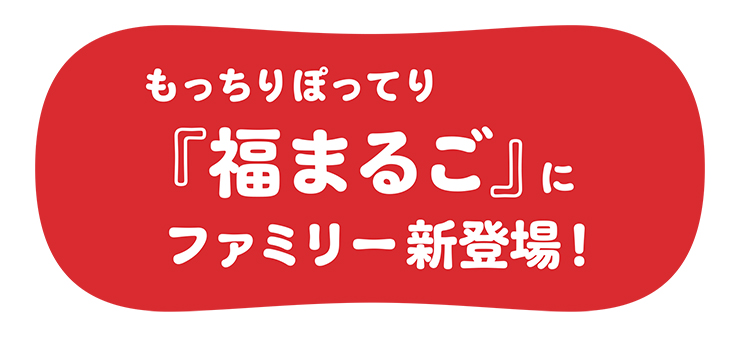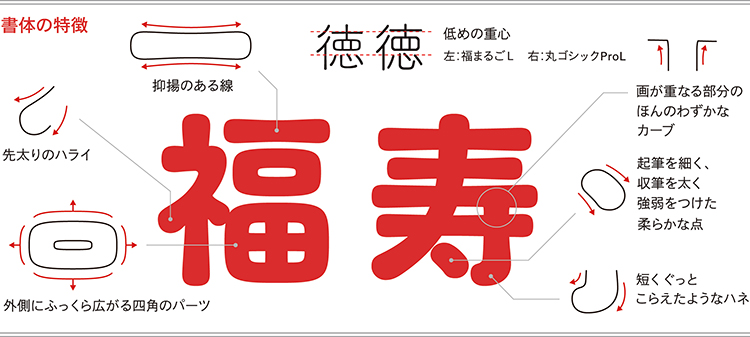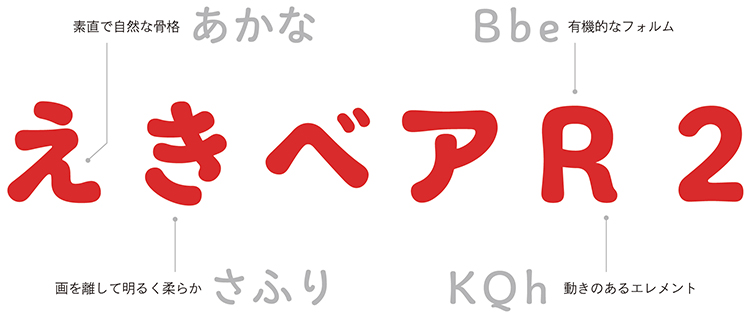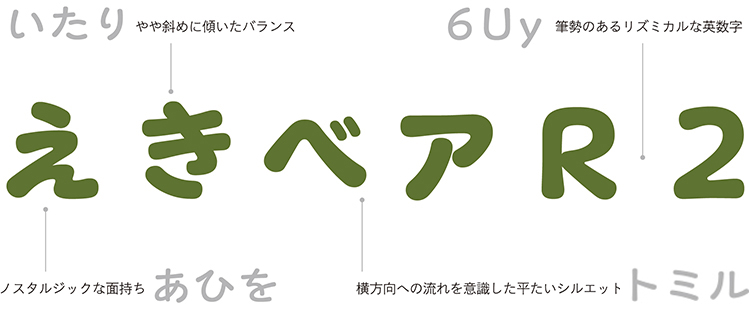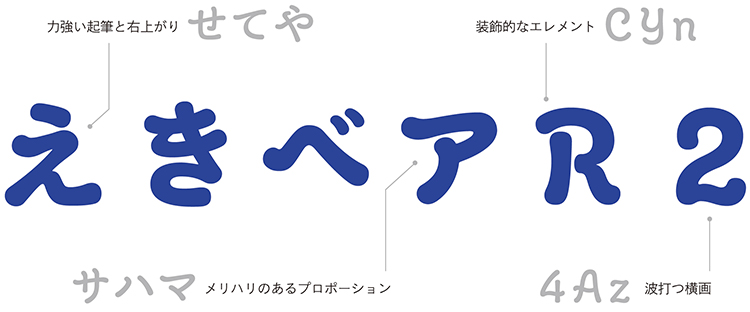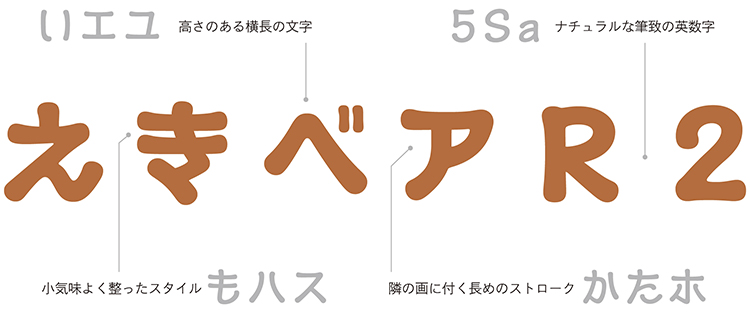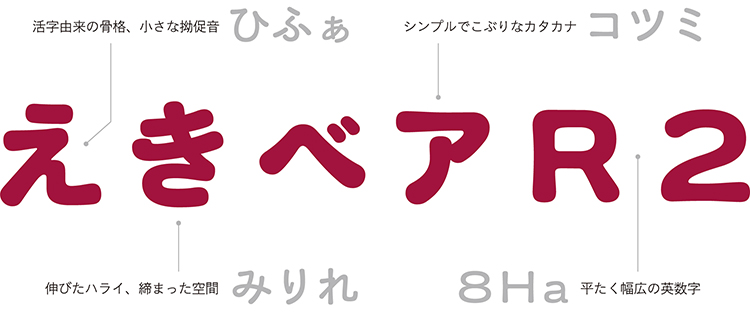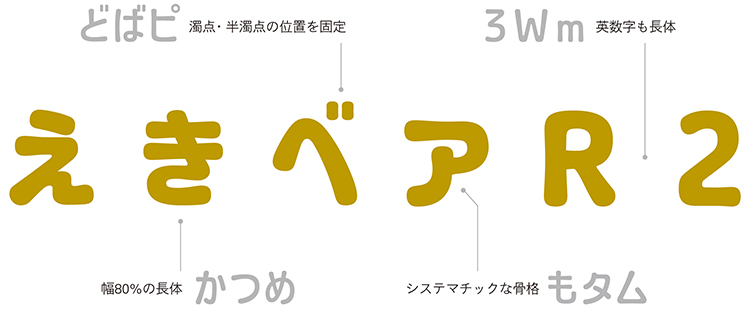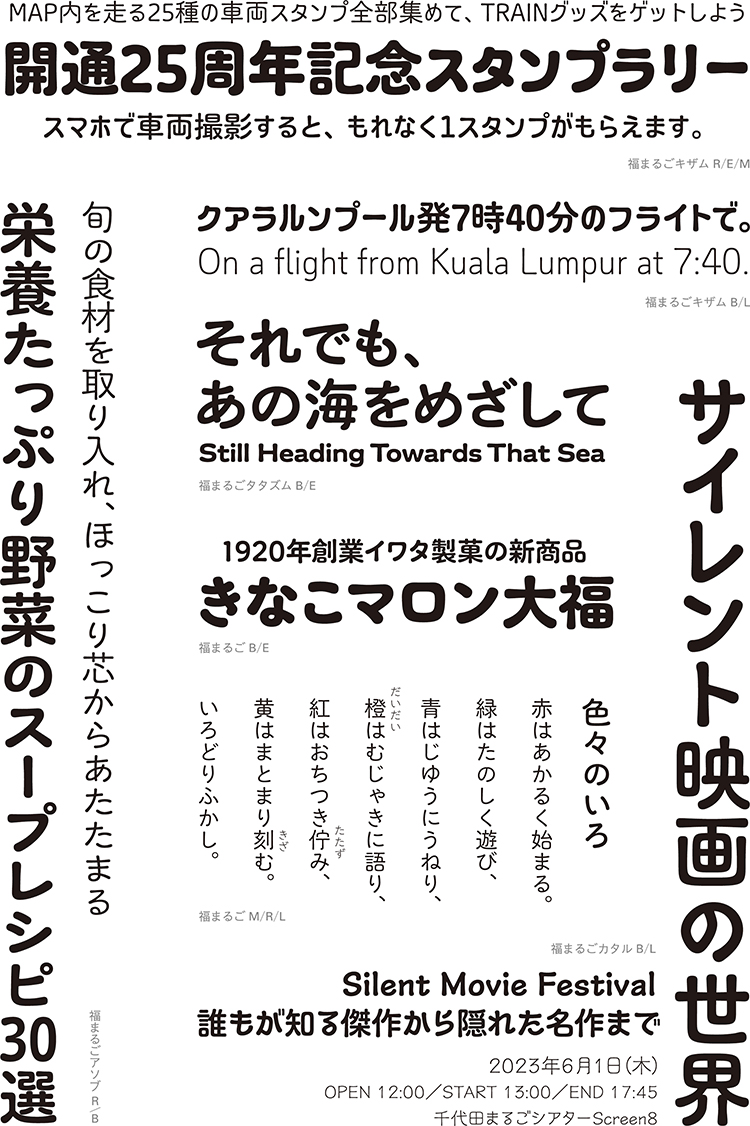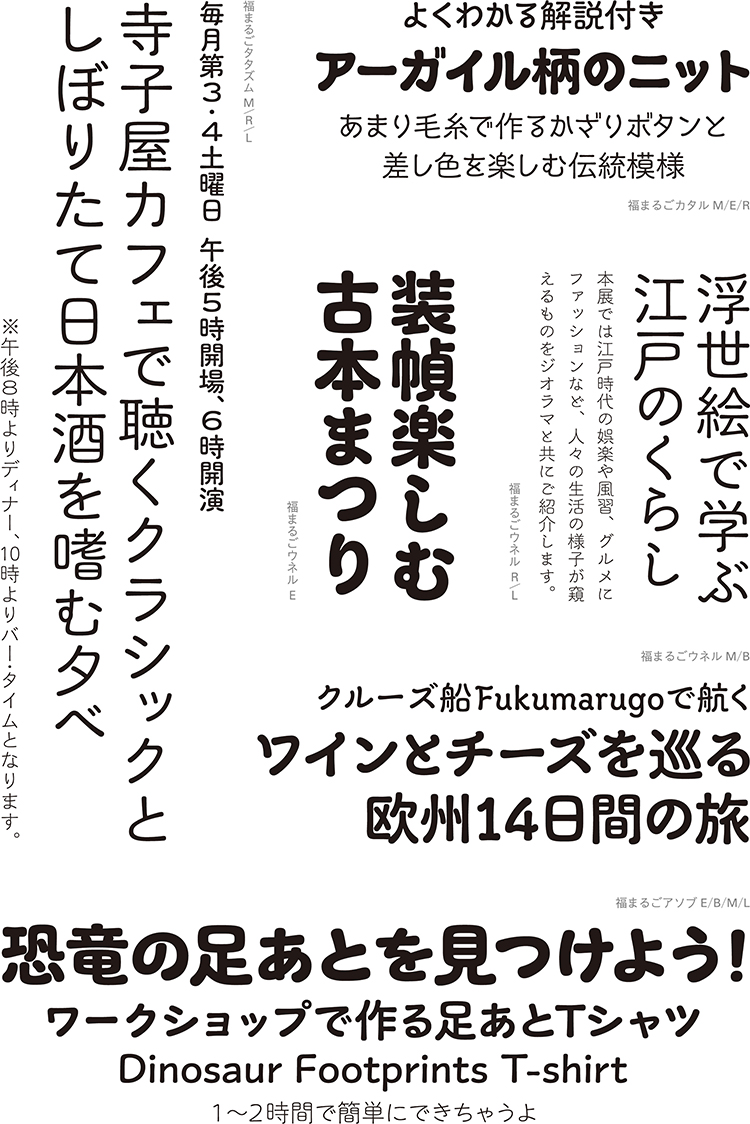
もっちりぽってり「福まるご」にファミリー新登場!
「次の100年も愛されるフォントを創る。」
2020年に創業100年を迎えた株式会社イワタが
同年に発表した「イワタ福まるご」はそんな思いから誕生しました。
そして2023年2月。かなにバリエーションを持たせた5書体が追加され、
「イワタ福まるごファミリー」となりました。
今回はオリジナルと新たに追加される5書体の魅力を紹介します!
イワタ福まるごとは
「イワタ福まるご」は全体に丸みを帯びたかわいらしいシルエットでありながらも上品な印象を与える丸ゴシック体です。
長文にも適した細いウエイトから、もっちりぽってりと豊かな丸みのある太いウエイトまで。全5ウエイトで展開する本書体は、SNSのテロップや映画、絵本のタイトルなど様々なシーンで使用される人気書体です。
書体の特徴
「イワタ福まるご」は、岩田母型時代の活字書体に独自の解釈を加えたオールドスタイルの丸ゴシックで、鉛活字の手書きや手彫り、インクにじみなどの有機的な曲線から着想を得た今までにないユニークな表情が特徴です。
1画1画に抑揚をつけた独特な表情でありながら、きちんと整った骨格で構成されています。
イワタ福まるご 書体の特徴図
イワタ福まるごオリジナル
『イワタ福まるごオリジナル』は見出しから長文組版まで広く使いやすいよう仮名はオーソドックスで読みやすい骨格に、欧文は有機的なフォルムでまとめています。
イワタ福まるごオリジナル 書体例
そして今回かなにバリエーションを持たせた5書体が加わり、現在販売中の書体(オリジナル)と合わせて「イワタ福まるごファミリー」となりました!
イワタ福まるごアソブ
『イワタ福まるごアソブ』はカジュアルさの中に軽快なリズムを持たせた書体で、親しみやすい遊び心に、ノスタルジックな面持ちも備えています。
その姿は原っぱで楽しく遊んだ少年時代を連想させます。
イワタ福まるごファミリー新書体1 見本
イワタ福まるごウネル
『イワタ福まるごウネル』は右上がりで華やかな書体です。装飾的な曲線を多く用いた芸術「アール・ヌーヴォー」から着想を得たデザインで、その様式は浮世絵からも影響を受けていると言われます。
イワタ福まるごファミリー新書体2 見本
イワタ福まるごカタル
『イワタ福まるごカタル』は映画字幕などで使われていた特徴的な文字をモチーフにした書体です。線画が長く高低差の少ない骨格と、線端の抑揚が手書きのイメージを伝えます。
レトロな映写機で映し出された名作が優しくゆっくりと語りかけるかのようです。
イワタ福まるごファミリー新書体3 見本
イワタ福まるごタタズム
『イワタ福まるごタタズム』は金属活字の古いゴシック体の骨格と幅広な欧文を合わせた書体です。味のあるアンバランスさや小さな拗促音など活字時代に培われたテイストを色濃く取り入れています。
時代を超えても色あせない重厚な佇まいは、夕日に染まった富士山を彷彿とさせます。
イワタ福まるごファミリー新書体4 見本
イワタ福まるごキザム
『イワタ福まるごキザム』は水平垂直に構成された長体かなを、横方向のラインに沿って揃えた機械彫刻のような書体です。
タイプライターで規則正しく打たれたような律儀さに柔らかい曲線が合わさり、整然としていながら堅苦しくない印象を刻みます。
イワタ福まるごファミリー新書体5 見本
書体見本
イワタ福まるご 書体見本1
イワタ福まるご 書体見本2